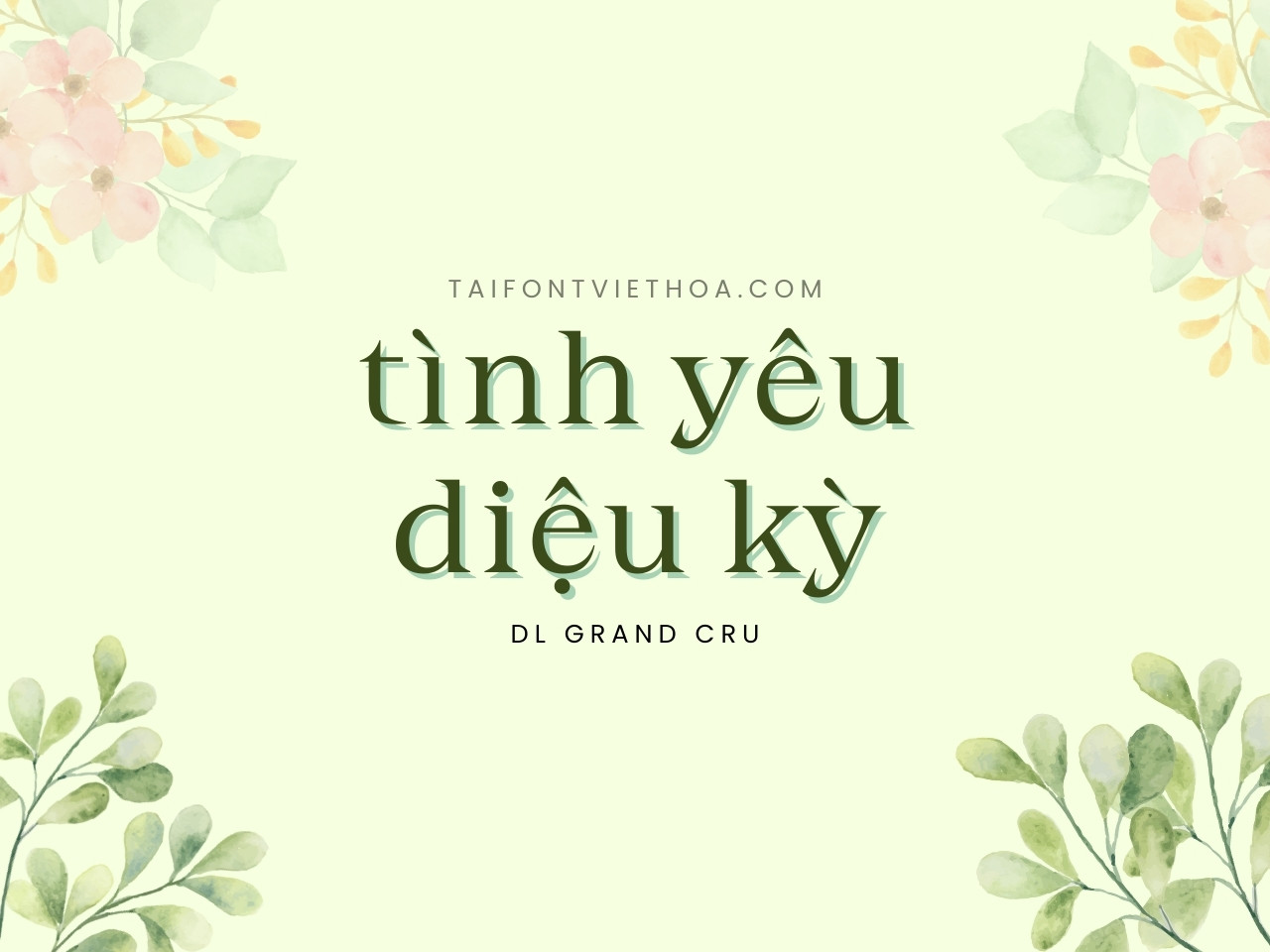
Font việt hóa DL Grand Cru
Tác giả Font: Emil Karl Bertell
Giới thiệu về font DL Grand Cru và phiên bản Việt hóa
DL Grand Cru là bản Việt hóa hoàn chỉnh của font “Grand Cru” – một thiết kế serif tinh xảo từ nhà thiết kế Fontfabric nổi tiếng, được phát hành vào năm 2020. Grand Cru mang phong cách editorial hiện đại kết hợp với vẻ cổ điển sang trọng của các font serif truyền thống châu Âu. Font hỗ trợ hơn 90 ngôn ngữ trên toàn cầu và được sử dụng rộng rãi trong các thiết kế về rượu vang, ẩm thực cao cấp, thời trang và tạp chí.
Phiên bản Việt hóa được thực hiện trọn bộ với đầy đủ các trọng lượng và style, hỗ trợ tiếng Việt hoàn chỉnh. Font đã được tinh chỉnh tỉ mỉ các ký tự dấu, giữ lại toàn bộ tinh thần cao cấp và nhấn mạnh sự thanh lịch trong từng nét chữ. Taifontviethoa.com đã sưu tầm, chọn lọc và đưa vào bộ sưu tập để phục vụ cộng đồng designer Việt Nam, mang đến giải pháp lý tưởng cho các dự án thiết kế cần phong cách sang trọng và bản sắc thương hiệu.
Đặc điểm thiết kế và khả năng ứng dụng
DL Grand Cru sở hữu các đường nét serif truyền thống pha lẫn hiện đại, với phần đuôi chữ tinh tế và độ tương phản cao giữa các nét dày – mảnh. Các glyphs có độ mở rộng hợp lý giúp dễ đọc ở nhiều kích thước. Font đi kèm với nhiều alternates và ligatures, mang đến sự đa dạng khi trình bày tiêu đề, đoạn văn hoặc hệ thống nhận diện thương hiệu.
Font này đặc biệt phù hợp với các ngành như rượu vang, mỹ phẩm cao cấp, nhà hàng fine-dining, tạp chí thời trang, bao bì thực phẩm cao cấp, cũng như hệ thống nhận diện thương hiệu đòi hỏi sự chỉn chu và khác biệt. DL Grand Cru là lựa chọn lý tưởng cho các nhà thiết kế đang tìm kiếm một font serif sang trọng mang đậm chất châu Âu.